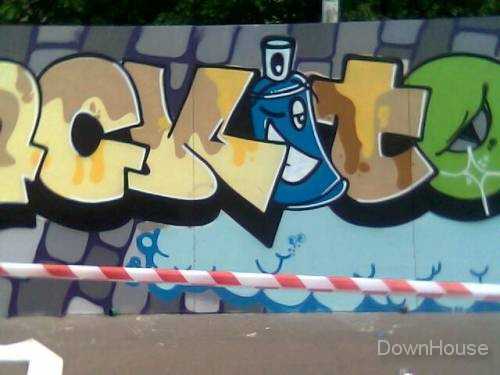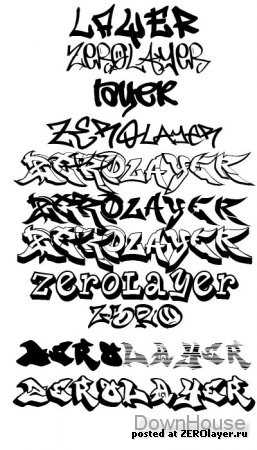
Шрифты граффити для бомбинга – Шрифт Bombing Скачать
Граффити-Бомбинг
Bombing относится к одному из самых экстремальных видов граффити. Это связано с тем, что бомберы предпочитают расписывать запрещенные или охраняемые объекты, сознательно нарушая установленные нормы. Собственно сам рисунок, выполненный в спешке на скорую руку, и называется «бомба». Для бомберов очень важно создавать свое творение на глазах изумленной и шокированной публики, таким образом формируя свой навязчивый фейм. Нередко авторы стараются поразить воображение масштабом рисунков, предпочитая раскрашивать поверхности больших размеров.
Возникновения бомбинга своими корнями уходит в Нью-Йоркскую подземку начала 70-х гг. прошлого века, когда местные райтеры окончательно облюбовали подвижной состав метрополитена в качестве объектов росписи. Начинается настоящая экспансия на вагоны метро, которые враз оказались заполоненными вызывающими надписями.
Условия, в которых происходит нанесение рисунка бомбером, диктуют свои особенности нанесения изображения. К ним можно отнести минимум элементов, крупные детали и использование всего 1—2 цветов. Наиболее популярные среди них — серебряный, черный, желтый и красный. Представители бомбинга просто не успевают уделять внимание мелким деталям, так как зачастую вынуждены быстро скрываться от полиции или представителей разъяренной общественности. От такой спешки страдает и качество, но к данному моменту все относятся с пониманием и делают на это скидку.
Выделившись в отдельное направление граффити, Bombing приобрел собственные шрифты. Один из них —»Блокбастер» представляет собой прямоугольные либо несколько наклонные буквы большого размера. Неудивительно, что их используют для создания гигантских надписей. Во время работы буквы внутри закрашивают красками, придавая композиции окончательные объем и размер. Другой шрифт «Баббл» имеет округлые формы, поэтому довольно универсален. Чаще всего его выполняют в черном и серебряном цветах, используя для обведения деталей. Раньше «Баббл» можно было встретить на многих поверхностях, но сегодня он все более утрачивает популярность.
По мере распространения Бомбинга постепенно стали появляться особые типы рисунков, отражающие специфику этого направления. К ним можно отнести Throw-up — создаваемое в быстром темпе изображение, внутри совсем не разрисованное либо заполненное лишь скорой штриховкой. В момент расцвета граффити в середине 70-х гг. Throw-up приобрел бешеную популярность. Вагоны метро были буквально усыпаны двухбуквенными именами героев невидимого фронта.
Также хорошо известен Quikpiese — наспех нарисованные картинки с плохо проработанными деталями и значительными огрехами. Как правило они представляют собой буквенные символы, выполненные в свободной манере. Действительно, для бомберов приоритетны скорость и количество элементов, нежели эстетическая и тем более искусствоведческая ценность.
Наиболее отчаянные представители течения порой подвергают себя смертельной опасности ради дозы адреналина, получаемого от запрещенного рисунка или надписи. К примеру, так происходит при росписи вагонов парижского метро на станции во время короткой остановки состава. Группа молодых людей стремительно бросается к вагонам и в течение минуты, к совершенному изумлению пассажиров, оставляет на боковой поверхности серию надписей, а потом стремительно исчезает. О том, что под ногами смертельное напряжение, похоже никто не думает.
Общество так и не успело дать однозначную оценку граффити-бомбинг. Одни считают это хулиганством, достойным сурового наказания, другие видят в этом своеобразное искусство и способ самовыражения. Несомненно одно. Сегодня все чаще можно встретить творения в стиле Bombing, что позволяет с уверенностью утверждать о продолжении существования экстремального движения.
Теггинг, граффити и трафареты
Это самое большое граффити которое есть в РОССИИ
Виды граффити
Тэггинг
Тэггинг – нанесение подписей (тэгов). Этот вид является наиболее простым и примитивным, поэтому им чаще всего занимаются подростки, но есть и тэггеры с весьма серьёзным стажем. Тэги обычно наносятся специальными маркерами с трудносмываемой краской, реже – аэрозольными баллончиками. Разновидностью тэггинга является скрэтчинг (от англ. to scratch – царапать, скрести) – выцарапывание надписей точильным камнем или наждачкой на стёклах и других подобных поверхностях. Надписи в стиле тэгов используются и в коммерческих целях – например, для создания логотипов.
Бомбинг
Бомбингом обычно называют любое нелегальное рисование на стенах, транспорте и т. п. Для этого чаще всего используют 2 типа шрифтов: баббл и блокбастер. Бабблом ( от англ. bubble – пузырёк) называется округлый тип шрифта, наиболее простой по исполнению. Такие шрифты обычно выполняются в двух цветах — серебряном (лучше всего подходит для закрашивания больших поверхностей) и чёрном (обведение). Сейчас баббл из-за своей примитивности считается уже немодным. Шрифт «блокбастер» (англ. – blockbuster – авиабомба, способная разрушить целый квартал) используют для создания особенно больших «кусков» (так на сленге называются шрифты). В этом случае буквы обычно прямоугольные (реже – наклонные), что позволяет закрашивать их не только баллончиками, но и обычной масляной краской с помощью кистей и валиков.
Райтинг
Райтингом (англ. to write – писать)у нас называют профессиональное граффити, а райтерами – профессиональных граффити-художников, хотя на Западе райтером называется каждый граффитчик. В профессиональном граффити (оформление клубов и т. п.) обычно используется два вида шрифтов. Wild style («дикий стиль») представляет собой трудночитаемое переплетение букв с помощью стрелок, ответвлений и других подобных элементов. Стиль 3D является самым сложным по исполнению и представляет собой композицию из трёхмерных букв и других элементов с плавным переходом одного цвета в другой, так что в результате создаётся ощущение объёмности композиции.
Орудие бомбера — естественно баллон, но не простой баллон, а с широкой насадкой. Тут такие линии, которые де-лает широкая насадка Sadolyn’a не подойдёт. Как минимум, для быстрого рисования надо сантиметра в 3-5. Меньше — уже сложнее.